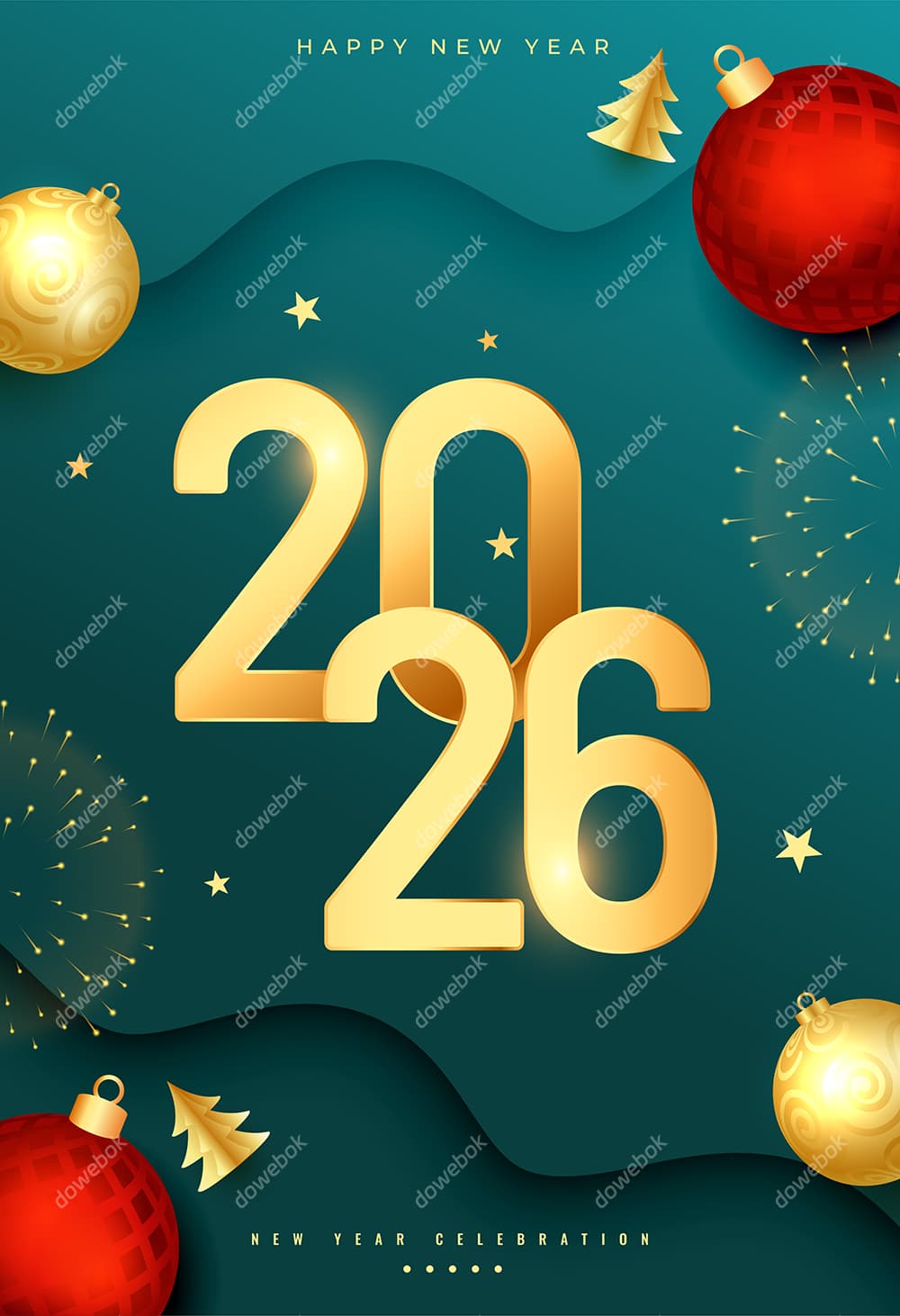
这是一款由圣诞装饰和金色数字设计的 2026 新年快乐海报矢量素材,青蓝渐变背景衬着波浪纹理,金色立体 “2026” 字体醒目华贵,周围点缀红金装饰球、金色小树与星芒烟花,上下配 “Happy New Year”“NEW YEAR CELEBRATION” 字样。红金与青蓝的碰撞既显节日喜庆,波浪纹理与装饰元素又添灵动氛围,适配新年贺卡、装饰物料,兼具温馨与精致感。